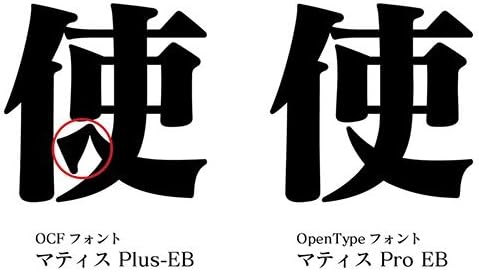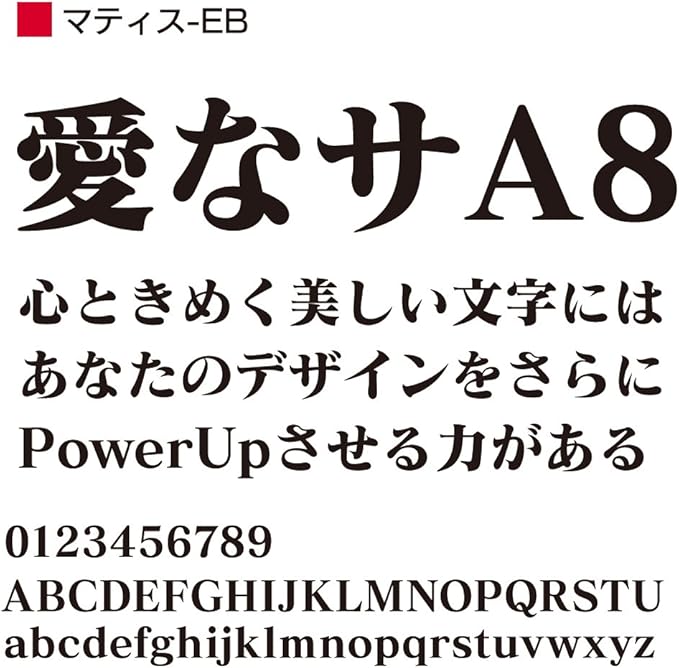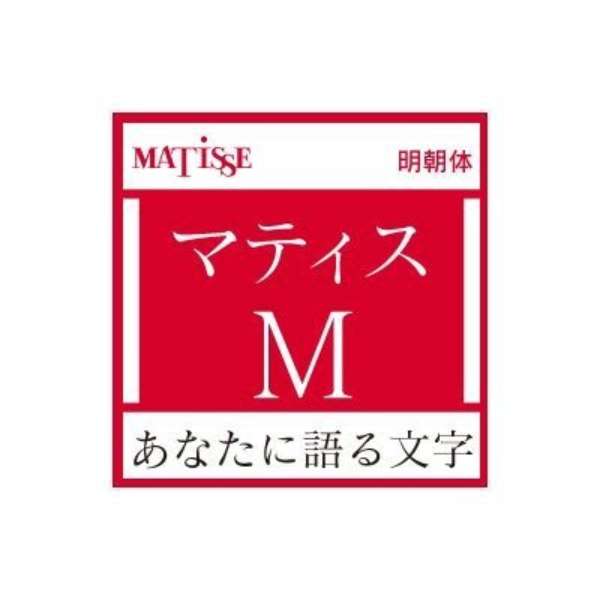
通常フォントというものは非常に高価な製品。 しかし、「マティスeb」を個人利用に限り4,600円(税別)という安価で提供する特別パッケージが、「エヴァンゲリオン公式フォント マティスeb版」です。 フォントワークス社のサイトから購入すれば、決済後にダウンロードでき、後日cdromと.
マティス フォント 購入. モリサワフォント様は1年で5万円、pc1台から。 morisawa passport エヴァンゲリヲンシリーズで有名なマティスフォントを提供しているフォントワークス様、本当に美しい使いやすいデザインのフォントを出されています。1書体1パッケージでだいたい税別18,000円。. エヴァフォント、マティスebを購入してみた こんにちはイマクです。 以前から欲しかったエヴァンゲリオンで有名な極太明朝体のフォントを購入しました! その名もマティスeb! さっそく使ってみたよ! エヴァフォント、マティスeb導入!. 規格 JIS X ;.
フォントワークスコレクションの中からクラシックシリーズ(全29書体)のダウンロード版 Windows用 OpenTypeフォント(単体製品)です。 収録書体名 明朝体「マティス ProDB」 仕様 Adobe Japan 14 Pro仕様(文字収録) 書体の特長. 下記のような個性派有料フォントが無償で使える場合もあります。 またこれらは一例ですので作品の雰囲気にあった素敵なフォントを使い分けてみてください。 マンガ制作におすすめな個性派有料フォント 『優雅にキラキラ』なイメージ マティスえれがんと. フォントワークスコレクションの中からクラシックシリーズ(全29書体)のダウンロード版 Mac用 OpenTypeフォント(単体製品)です。 収録書体名 明朝体「マティス ProM」 仕様 Adobe Japan 14 Pro仕様(文字収録) 書体の特長.
どうも。エヴァが放送されたときリアルで14歳でA10神経全開だった、するぷ( @isloop )です。 先日、ついにエヴァに使われているフォント「マティス Pro EB」(通称俺明朝)を購入しました。 しかし、このフォントをそのまま使うとどうもエヴァっぽくないのです。. マティス(Matisse)は、フォントワークスが発売した明朝体およびそのフォント製品。 デザインはロダンを手がけた佐藤俊泰による。 1991年にMacintosh DTP用PostScriptフォントとしてリリースされた。. 『エヴァンゲリオン公式フォント マティスEB TrueType 版』が11月10日にフォントワークスより発売開始! 「新世紀エヴァンゲリオン」で印象的なあの書体“エヴァ明朝”が、PC フォントとして利用可能に!.
エヴァスタンプの第5弾は「エヴァ文字」でおなじみ公式フォント「マティスeb」のスタンプで登場!あの名セリフのほかにも使いやすい表現が満載! line store 限定 購入金額に対してline. こんにちは! Fmanです。 前回に引き続き、デザイン制作には欠かせないフォントついて。 前回のブログ:(フォントを語る上で知っておきたい基礎知識10) プロのデザイン制作現場では、良質なフォントが無いとまず戦えません。. 使用フォント マティス ProN ファミリー 洗練された、高級感のあるイメージを与える「マティス(明朝フォント)」を使用。 美しいフォントを使って文字を活かすデザインにチャレンジ。 背景写真のうえで文字が引き立ち、インパクトを与えます。.